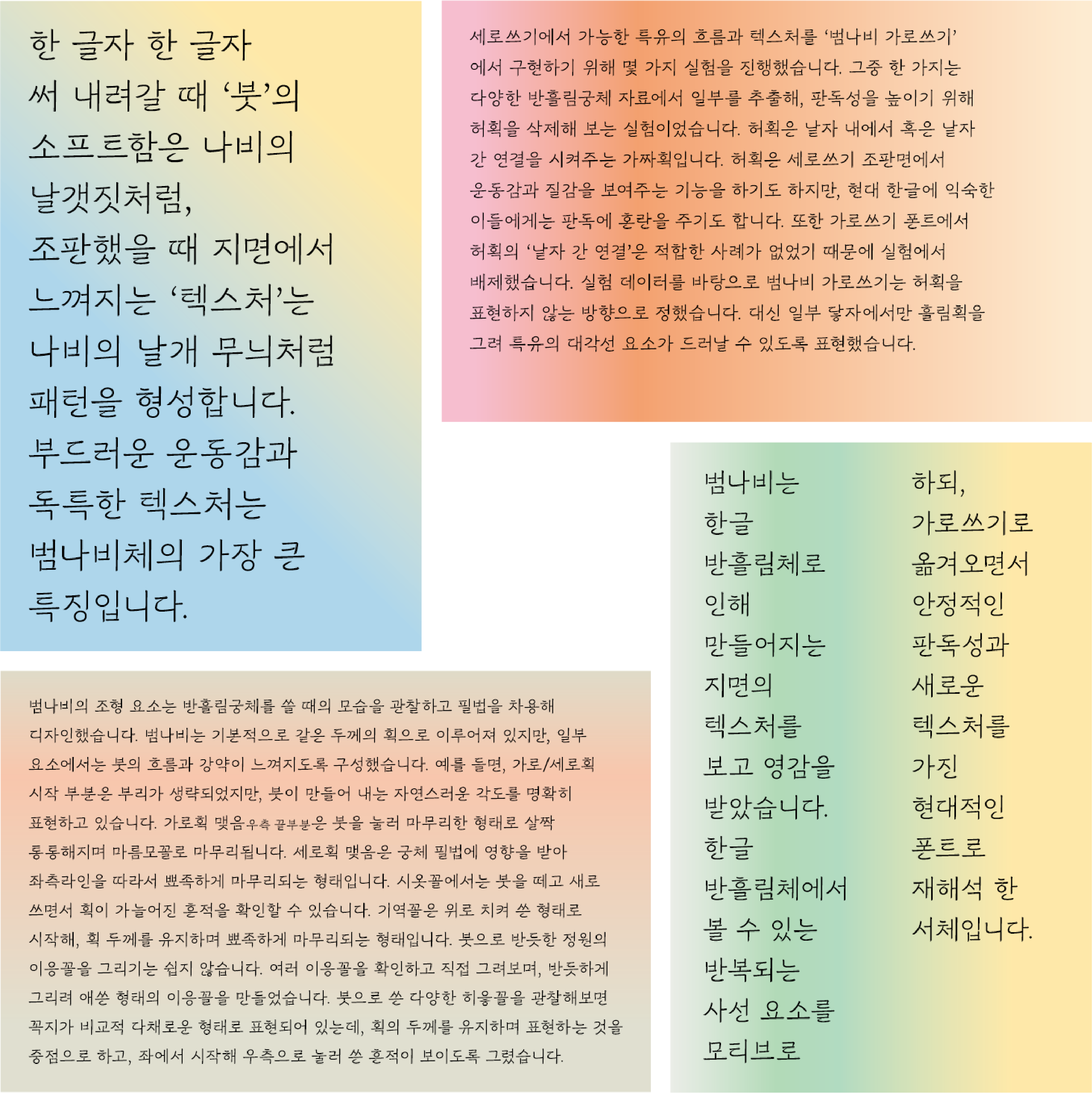
" 한 글자 한 글자 써 내려갈 때의
'붓'의 소프트한 움직임은 나비의 날갯짓처럼,
조판했을 때 지면에서 느껴지는 '텍스처'는
나비의 날개 무늬처럼 패턴을 형성합니다."
최근 일곱 번째 한글글꼴창작지원사업 결과물
<범나비 프레젠테이션> 전시를 성황리에 마친
서체 디자이너 이주현.
그가 그리는 서체와 닮아
유려하고도 곧은 모습이 엿보이는 이주현 디자이너.
글자 그리고 <범나비>를 주제로 이야기 나누었습니다.
01
폰트 디자이너 이주현
안녕하세요. 서울에서 코스모프타입을 운영하는 타입 디자이너 이주현입니다. 레터링과 폰트 작업을 하고 있으며, 온/오프라인 강의를 주로 하고 있습니다.
스튜디오에서는 주로 자체 제작한 폰트를 판매하거나 의뢰받아 글꼴을 만들고 있습니다. 올해 초에 스튜디오에서 제작한 '포치니' 폰트를 만들어 판매 중이고, 향후 범나비를 포함한 다양한 폰트를 출시할 계획입니다. 정기적으로 글꼴 관련 워크숍도 진행하고 있어요.
이주현과 범나비
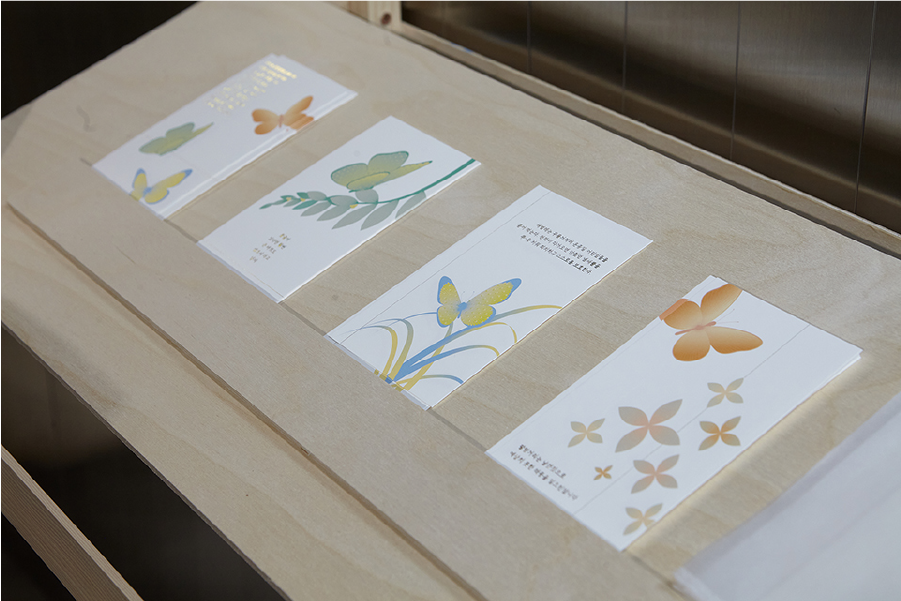
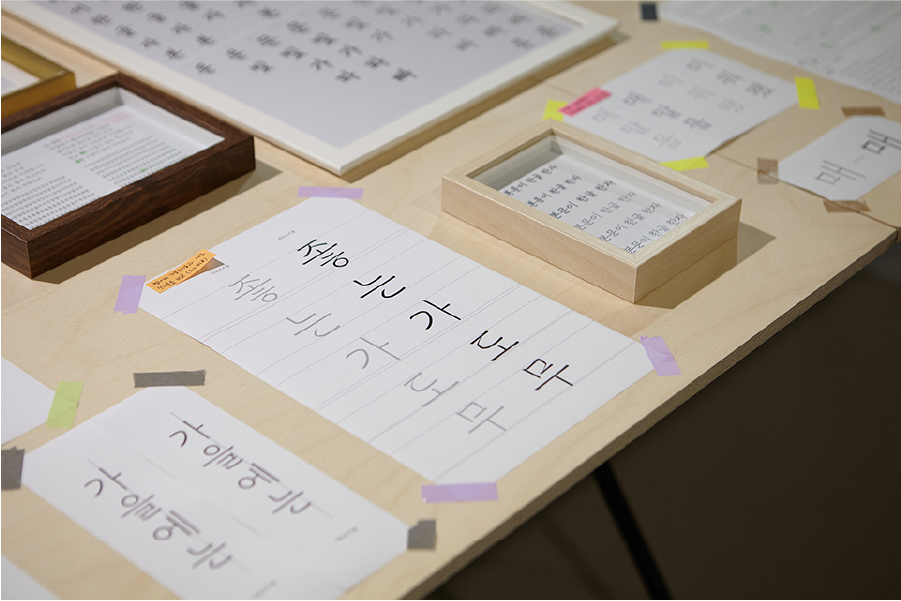
전시, wrm space에서의 <범나비 프레젠테이션>, 2023
🎤 얼마 전 일곱 번째 한글글꼴창작지원사업 결과물인 <범나비>를 출시하셨어요. <범나비>는 어떤 서체인가요?
범나비는 한글 반 흘림체로 인해 만들어지는 지면의 텍스처를 보고 영감을 받은 서체입니다. 한글 반 흘림체에서 볼 수 있는 반복되는 사선 요소를 모티브로 하고 있어요. 반흘림체의 분위기를 가로쓰기로 옮겨오면서 안정적인 판독성과 새로운 질감를 가진 현대적인 폰트로 재해석한 서체입니다. 웨이트는 현재 5~6개 정도로 계획하고 있고, 이번 전시에서는 가장 얇은 Light를 중심으로 하고, 가장 두꺼운 Black도 일부 선보였습니다.
🎤 글꼴의 이름을 지은 이유와 제작 계기, 기획단에 대한 설명을 부탁드립니다.
서체의 독특한 텍스처를 바로 떠올릴만한 이름으로 짓고 싶었습니다. 맘에 드는 이름을 짓기 위해 고민해왔는데, 범나비(호랑나비)가 가진 부드러우면서 강렬한 텍스처가 비슷하다고 생각했습니다. 한 글자 한 글자 써 내려갈 때 '붓'의 소프트한 움직임은 나비의 날갯짓처럼, 조판했을 때 지면에서 느껴지는 '텍스처'는 나비의 날개 무늬처럼 패턴을 형성합니다. 부드러운 운동감과 독특한 텍스처가 닮아 있어 범나비로 네이밍 하게 되었습니다.
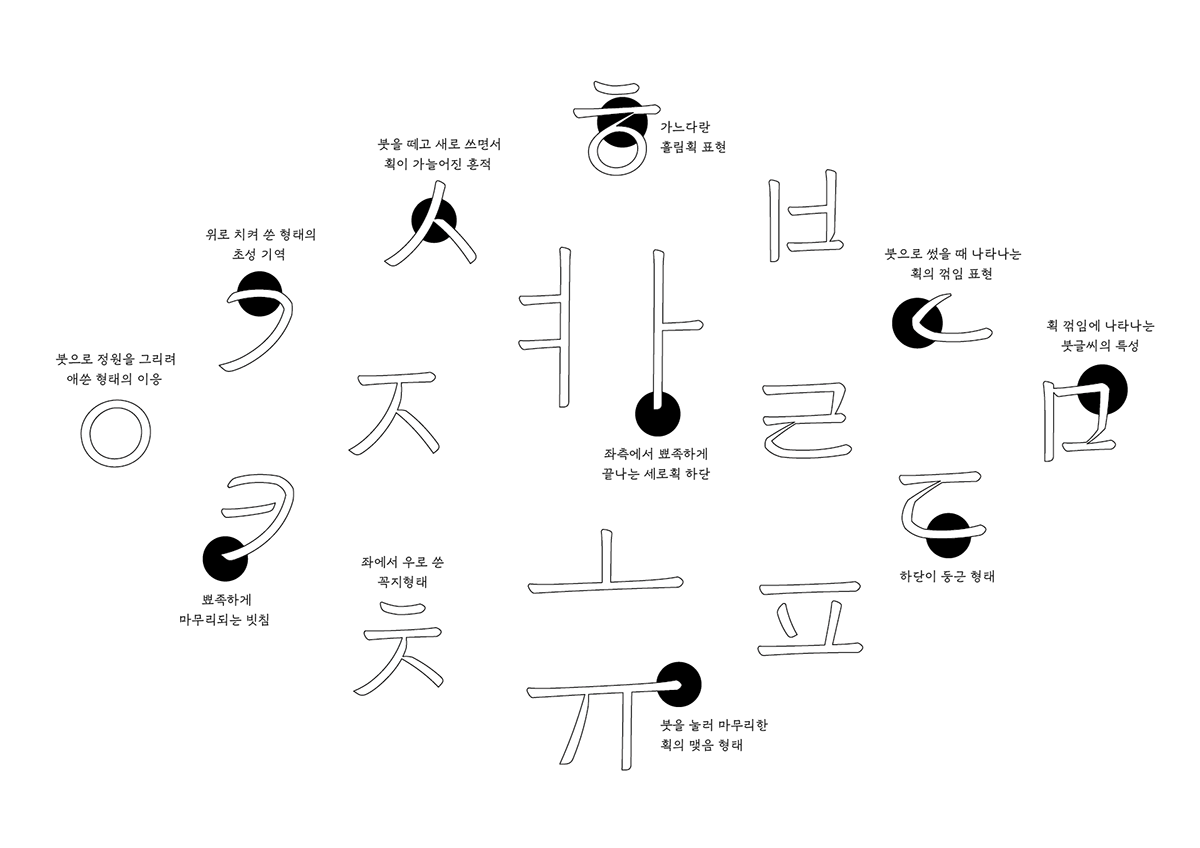
<범나비>의 자소특징
🎤 <범나비>에서 특히 신경 쓴 부분, 또는 뽐내고 싶은 특징을 꼽아주신다면?
붓글씨의 특징을 반영한 부분이 있는데, 비교적 색다른 느낌이지만, 읽었을 때 자연스럽게 흘러갑니다. ㄴ, ㄷ 등의 꺾임, 굴린 부분이나 초성 ㄱ을 둥글게 처리한 부분 등이 해당합니다. 또 범나비에는 사선요소가 전체적으로 들어가 있는데, 긴 문장을 썼을 때 반복되는 사선 요소가 느껴지면 독특한 분위기를 줍니다.
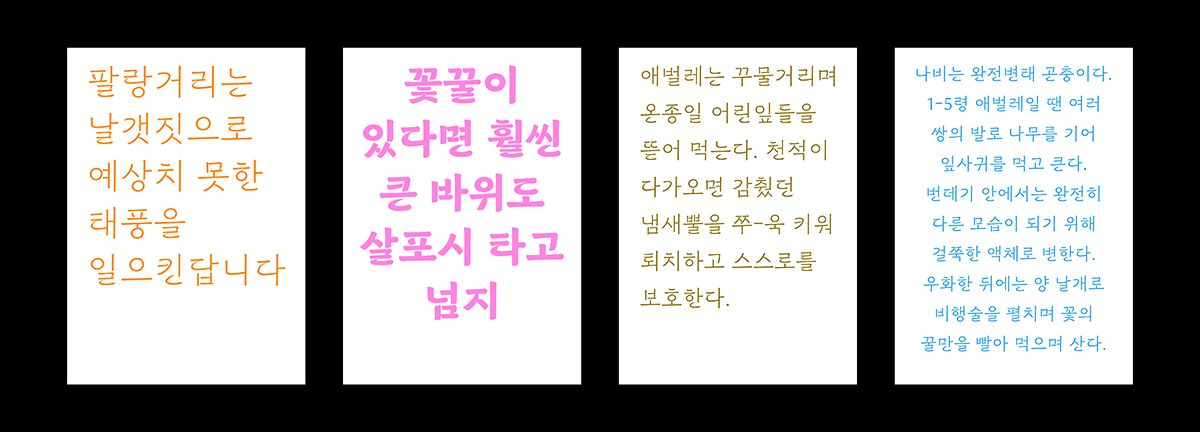
전시, wrm space에서의 <범나비 프레젠테이션>의 팬그램 포스터, 2023
🎤 wrm space에서 지난 8/3 - 8/13, 10일의 기간 동안 전시를 진행하셨어요! 해당 전시에서는 <범나비>만의 팬그램 문장을 만드셨다고 알고 있습니다. 문장에 대한 소개 부탁드립니다.
전시의 형태로 서체를 보여줘야 해서 고민이 많았습니다. 폰트 디자인 씬에 있는 '팬그램' 문화를 소개하면 관람객이 좀 더 글꼴을 흥미롭게 볼 수 있을 것 같았습니다. 나비의 생애와 주요 특징에 대한 텍스트를 읽고 상상력을 촉발하는 상황들을 추려 문장을 만들었습니다. 모든 닿자를 넣으면서도 문장을 자연스럽게 구성하는 것이 쉽지만은 않았는데, 완성된 문장을 읽다 보면 기분 좋은 에너지가 느껴진다고 생각합니다.
주황색과 핑크색 포스터에는 ㄱ부터 ㅎ까지를 모두 넣었습니다. 금색과 하늘색 포스터에는 쌍닿자(ㄲ, ㄸ, ㅃ, ㅆ, ㅉ) 다섯 개까지 넣었습니다. 실제로 전시장에서 팬그램 설명해 드리니 좀 더 자세히 살펴보시더라고요.
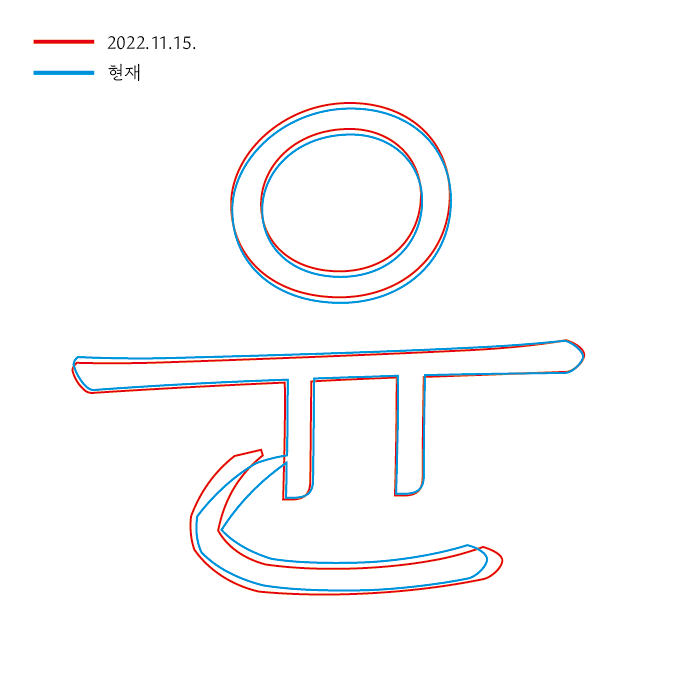
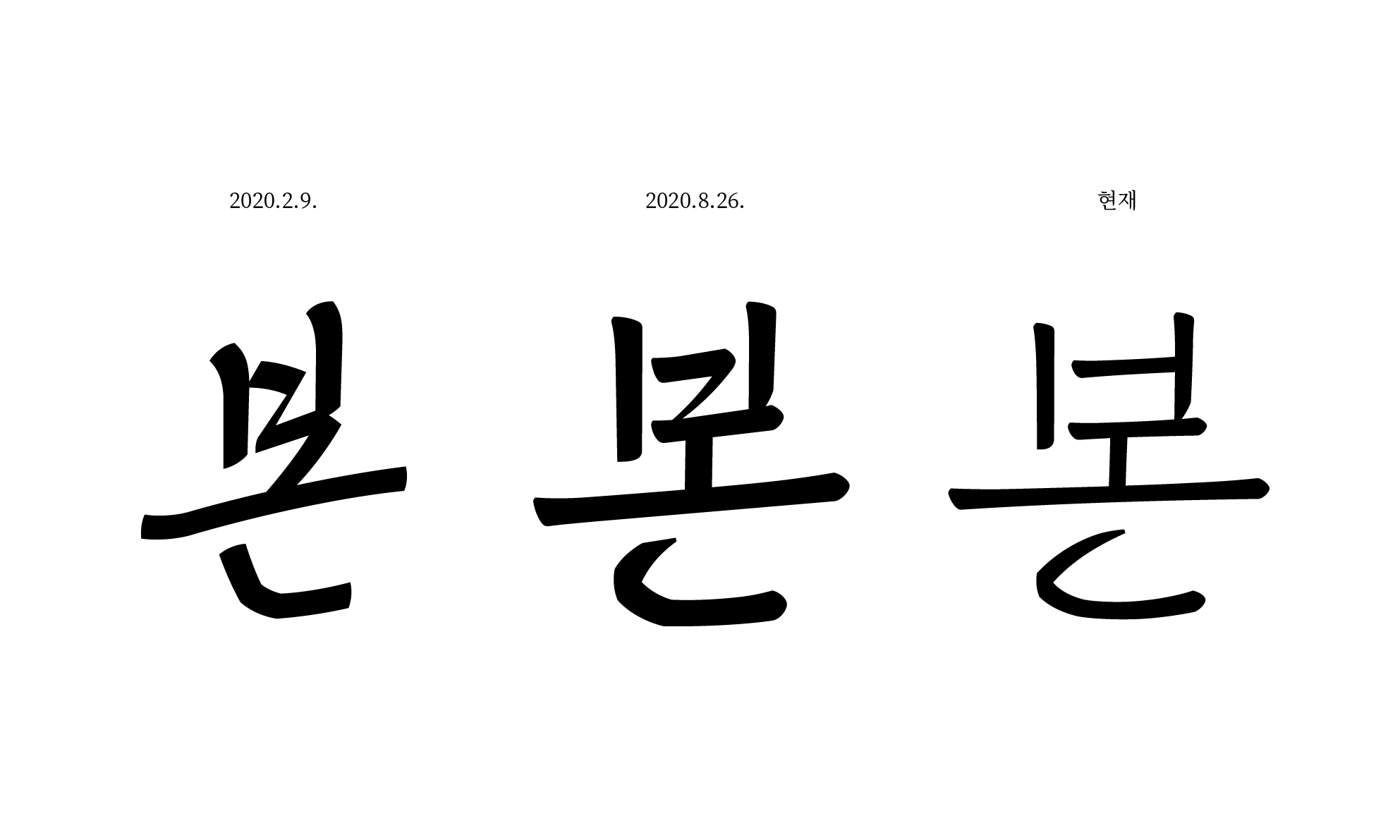
<범나비>의 작업 및 수정 과정, 2023
🎤 <범나비> 프레젠테이션 전시에서는 서체를 제작하시면서 수 없이 고민하고 수정하신 흔적들을 확인할 수 있었습니다. 본문용 폰트를 제작하시면서 중점적으로 수정하신 부분이 있다면?
본문용이라는 용도에 대한 고민을 가장 치열하게 했던 것 같아요. 제 개인적인 취향과 해석을 표현하면서도 긴 텍스트에서, 다수의 눈에도 만족스러운 형태를 찾기가 힘들었습니다. 예를 들면 가장 큰 특징 중 하나인 받침 ㄴ은 개성이 강한 편이라 똑바로 세운 형태도 좋겠다는 의견도 있었습니다. 개성과 본문용은 양립할 수 없는가에 대해 나름의 도전을 해본 것 같아요. 다양한 각도, 디테일을 테스트해 보며 지금의 형태로 마무리했습니다.
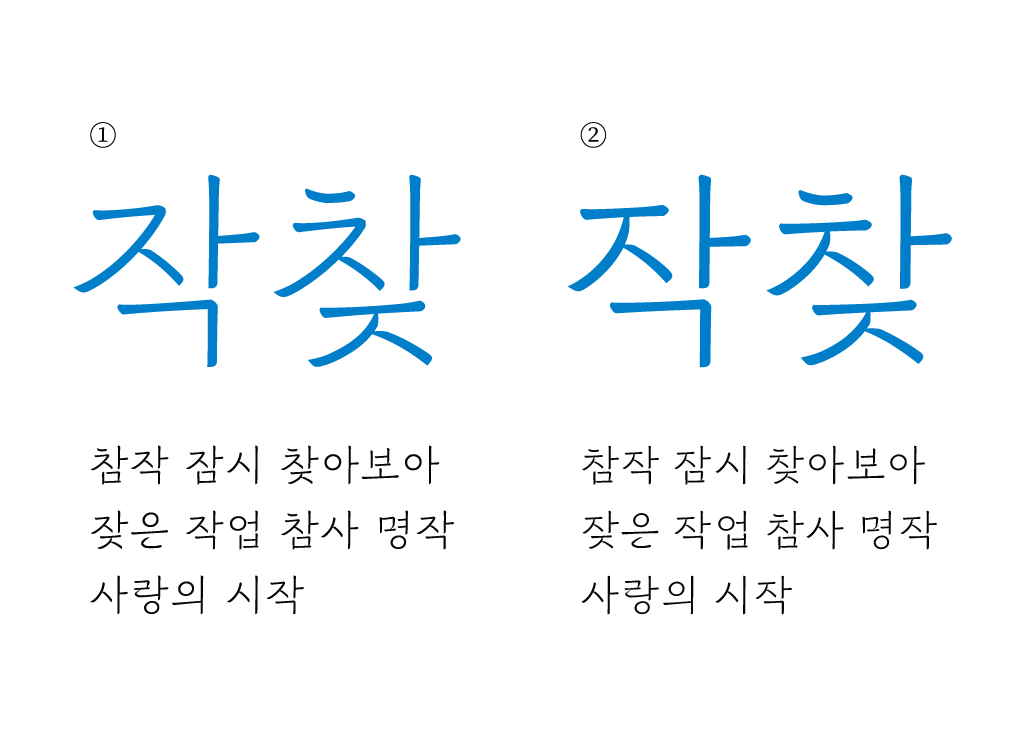
<범나비>의 수정 과정, 2023
🎤 <범나비> 제작 중 어려웠던 부분이 있으셨나요? 어려움을 극복하신 과정이나 에피소드를 들려주세요.
세로쓰기의 조형 요소를 가로쓰기로 옮겨오면서 시행착오가 많았습니다. 참고했던 자료를 따라 그려보기도 하고 관찰하면서, 세로쓰기에서의 글자 크기와 비율, 시각 보정 등이 확연히 다르다는 걸 느꼈어요. 조형 요소를 제외하고 거의 모든 요소를 가로쓰기용에 어울리도록 테스트했습니다. 크기, 비율, 시각 중심, 흐름 등 가로쓰기용 본문체로 만드는 데 노력을 기울였습니다.
이 과정에서 혼자만의 실험도 있었지만, 주변의 도움을 많이 구했던 것 같아요. 특히 같이 일했던 분들이나 다른 분야의 디자이너들에게 조언을 구하면서 만들었습니다.
전시, <범나비 프레젠테이션> 포스터, 2023
🎤 2년 동안 공들여 작업하신 <범나비>. 어떻게 쓰이기를 기대하시나요?
전시 포스터에서도 의도한 부분이 있는데, 한국적인 이미지와 잘 어울리는 것 같습니다. 본문용으로도 물론 쓰임을 기대하지만, 써본 분들은 디스플레이용으로도 괜찮을 것 같다고 의견을 주셨습니다. 폰트를 사용하는 분의 상상력으로 다양하고 새로운 곳에서 많이 봤으면 하는 바람입니다.
🎤 저도 얼른 <범나비>를 써 보고 싶은데요. 추후 범나비의 행보는 어떻게 될까요?
향후 계획은 최소 2~3종 정도 우선 만든 후 출시할 예정입니다. 현재는 가장 얇은 Light와 가장 굵은 Black을 작업하고 있습니다. 올해 1차 출시가 목표라 최선을 다해 일정을 맞추려고 합니다.
이주현의 지금
🎤 서체를 제작하시면서 영감은 어디에서 얻으시나요?
여행 갔던 곳의 간판, 길을 걷다가 만난 희한한 모양의 낙서, 지인의 손글씨, 오래된 책 등 다양한 곳에서 영감을 받습니다. 작업에 몰두하지 않고, 휴식하거나 힘을 빼고 있을 때 오히려 더 잘 보이는 것 같아요.
🎤 눈여겨보는 서체 디자이너 또는 스튜디오나 기업이 있으시다면?
최근엔 fttg 스튜디오의 작업에 빠지게 된 것 같아요. 이번 전시에서 협업한 fttg 스튜디오의 김지혜 디자이너와 종종 만나면서 디자인 이야기를 많이 하게 되었어요. 오래전 알게 되었을 때부터 색감을 정말 잘 쓴다고 생각했었는데, 이번 전시에서도 색감을 잘 뽑아서 감탄하며 작업했습니다.
<범나비>의 스케치 이미지, 2023
🎤 손 스케치와 디지털 작업의 비중은 어느 정도인가요?
아이디어가 필요하거나 밑그림이 필요할 땐 무조건 손 스케치를 진행합니다. 손으로 했을 때 느낌을 빠르게 보고 판단할 수 있습니다. 작업 초기에 대부분은 손 스케치를 진행하는 것 같아요. 또 작업 중간중간 수정할 때도 빠르게 스케치해 보기도 합니다. 디지털 작업의 비중이 물론 훨씬 높지만 새로움을 만들어내는 것은 손 스케치 작업이기 때문에 중요도는 거의 비슷할 것 같아요.
ELLE, <Please Stay> 레터링, 2023
🎤 폰트 작업 이외에도 레터링 작업을 자주 선보이시는데, 기억에 남는 레터링 작업을 꼽아주신다면?
최근에 ELLE 매거진의 <Please Stay> 칼럼에 들어간 레터링 작업을 흥미롭게 작업한 기억이 납니다. 저에겐 생소한 주제였는데, 작업하면서 알게 된 것도 많았습니다. 멸종 위기 동물들의 생김새와 이름을 찾아보게 되었고, 이름을 그리면서 차분하게 기후 위기 앞에서 제가 할 수 있는 실천을 해야겠다고 다짐한 계기도 되었습니다.
전체를 손 스케치로 하면서 개인적으로 색다른 시도였던 것 같아요. 작업 과정을 영상으로도 SNS에 올려놓았어요. 레터링 작업을 보며 누군가도 멸종 위기 동물과 기후 위기에 대해 한 번 더 생각할 수 있다면 좋겠습니다.
🎤 꾸준히 한글 서체 제작 실무 워크숍을 진행하고 계시는데요. 운영하시면서 느끼시는 소감이나 재미있는 부분을 공유해주신다면? 또, 다음 워크숍은 언제쯤일까요?
9월에 시작하는 레터링 워크숍을 계획하고 있습니다. 워크숍을 하면서 새로운 사람과 소통하는 것이 좋아요. 사람들의 요즘 생각을 알게 되어 저도 자극받기도 하고요. 무엇보다 누군가에게 필요한 도움을 줄 수 있다는 것이 즐겁습니다. 워크숍에서 글꼴 주제로 대화를 하게 되면 반짝반짝 빛나는 어떤 에너지가 느껴지는 것 같아요.
<범나비> 세로쓰기, 2023
🎤 현재 존재하지 않지만, 만들어보고 싶은 서체가 있다면?
범나비를 작업하면서 세로쓰기용 폰트에 관심을 많이 가지게 되었어요. 범나비 세로쓰기용 폰트는 아직 시도 중인데, 세로쓰기 했을 때만 가능한 특징들을 넣어 만들어보고 싶습니다. 이어쓰기라든지, 자폭이나 구조가 각기 다르다든지 하는 특징들이요. 세로쓰기 폰트의 시장성과는 별개로 개인적인 시도를 계속 이어가고 싶어요.